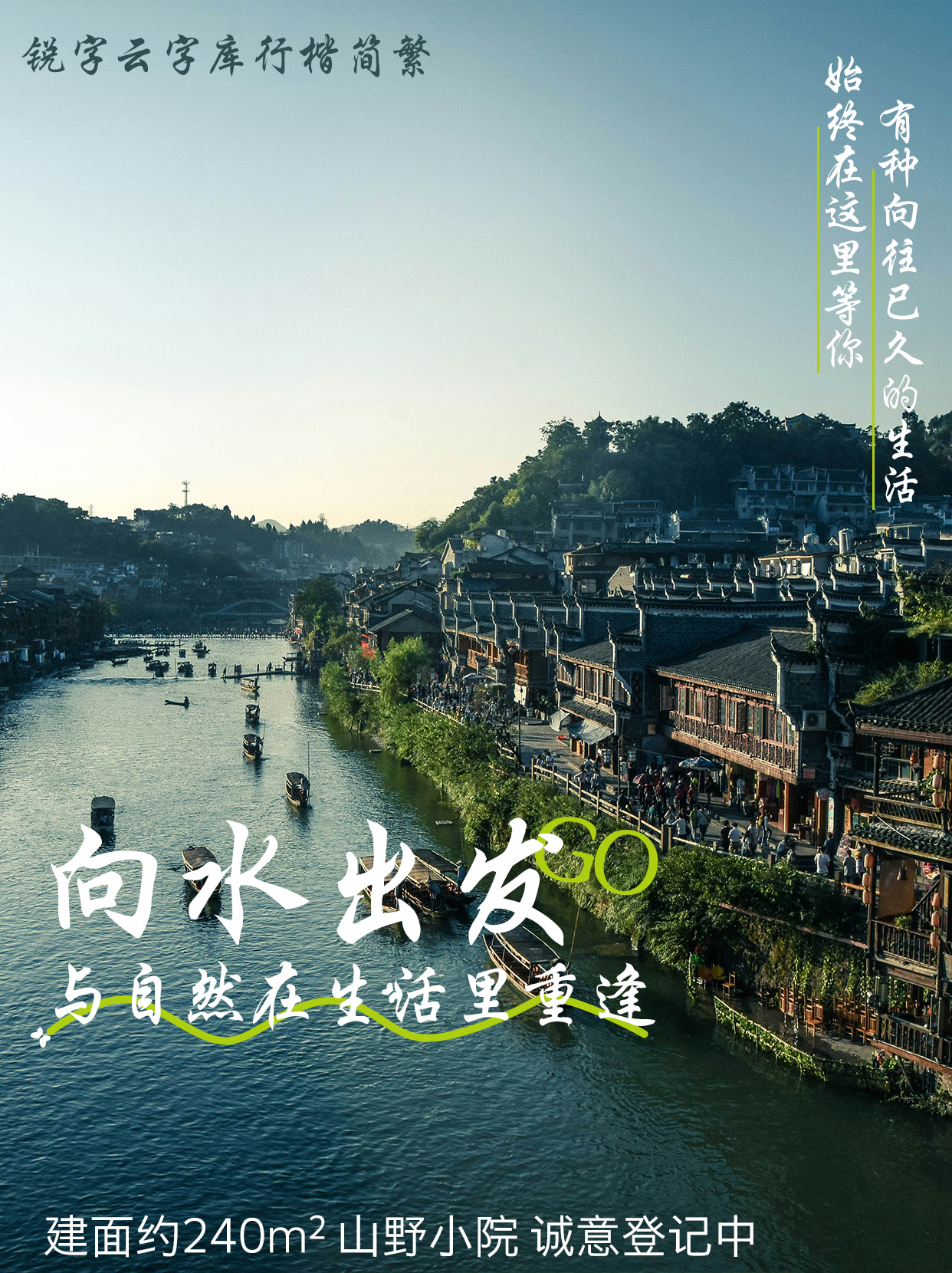
介于行书的活泼与楷书的端正之间的字体,造型秀美适意,笔画流畅,点画呼应,舒缓自如,读来如行云流水,一气呵成,具有较强的动势美感。楷行兼顾,直曲方圆收放有度,匀称呼应,连带适当,稳扎稳进。形体方正、笔画平直、结构严谨、字形定型。将楷书的体势、点画变得圆转连带、变化多样。略有行书的笔意自由,字的笔画可依据不同连笔位置的需要作出灵活多样的变化,起承转合,多取顺势,一笔带过。笔道流畅、潇洒多姿。